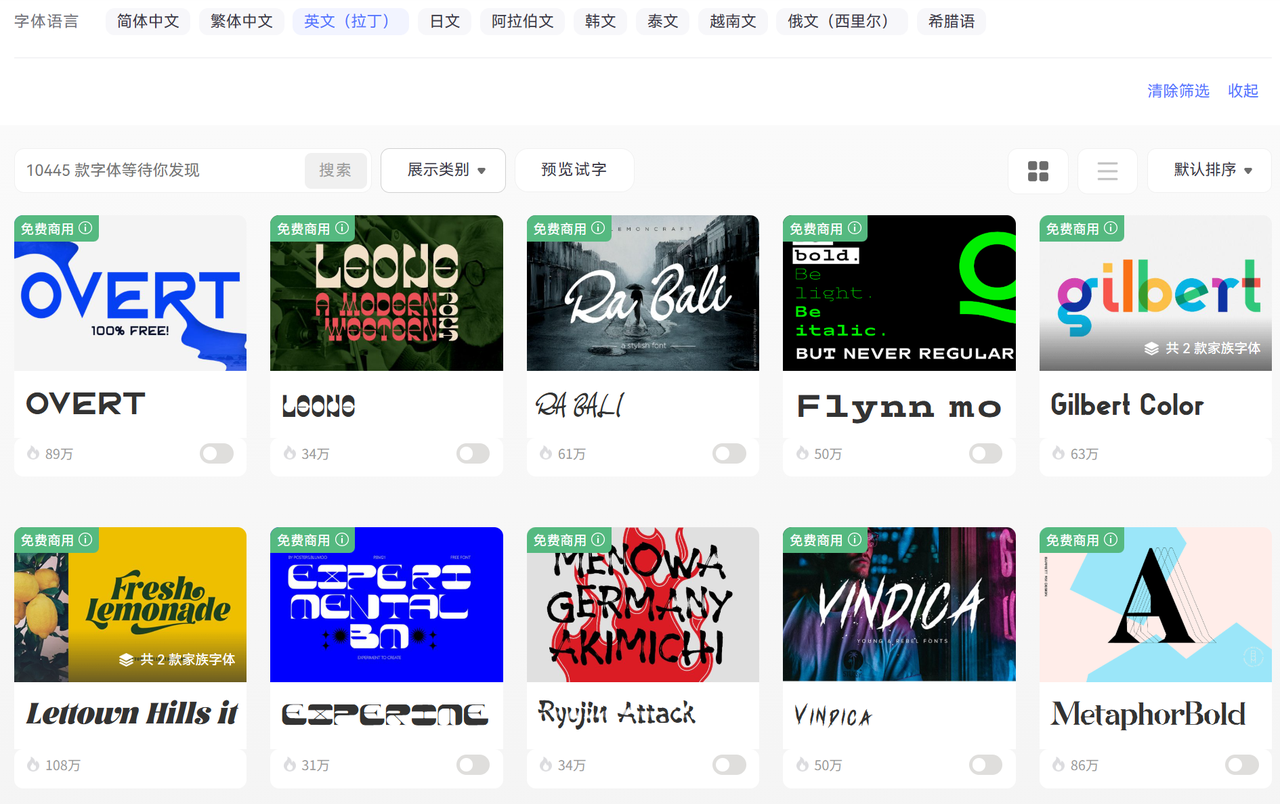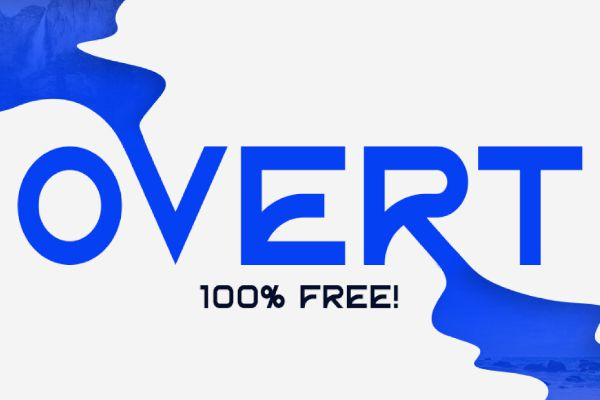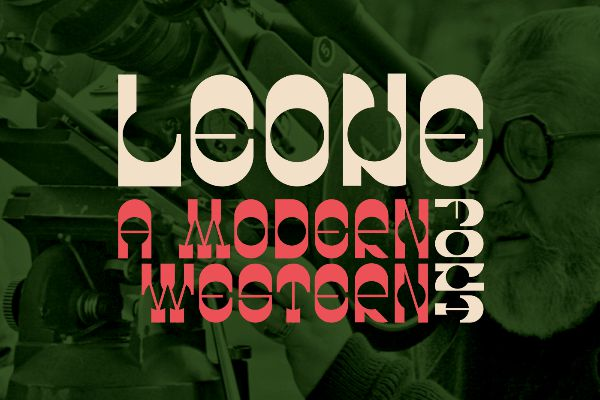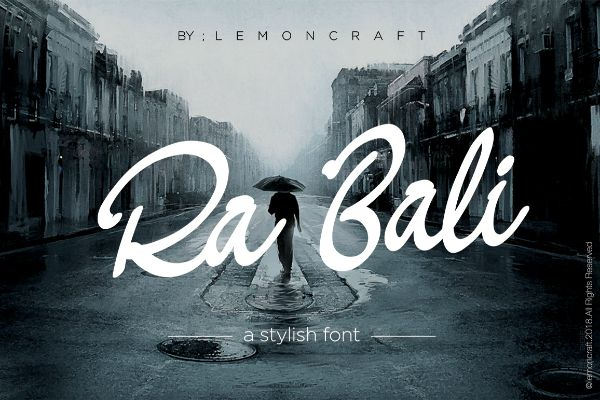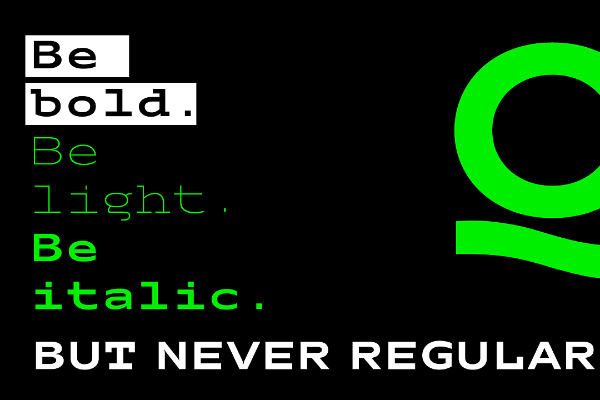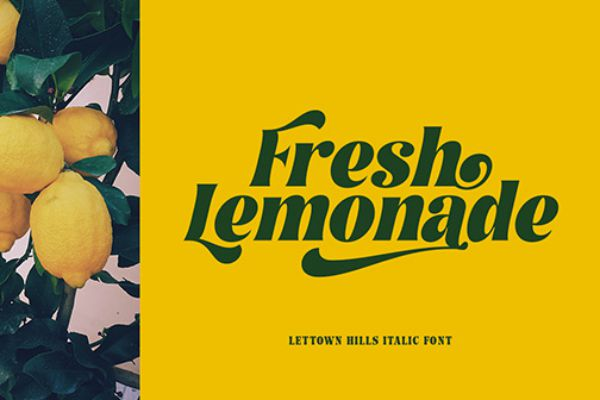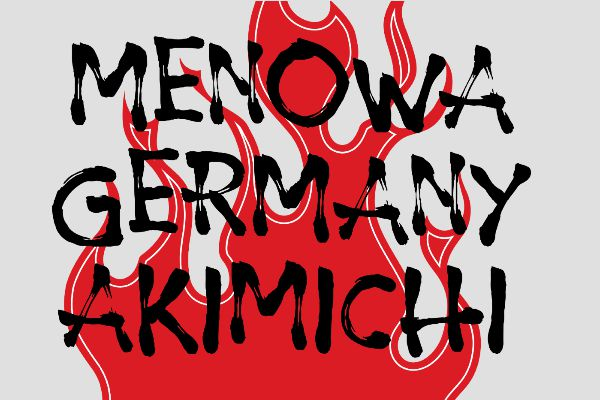
英文字体可以商用吗,分享 10 款免费商用的英文字体
不知道是否有小伙伴和我一样,觉得中文字体大部分都不可以免费商用,思考英文总不会有版权风险吧?其实都一样,大多数字体都是需要付费授权的,不能免费商用。不过今天我会给大家分享10 款可以免费商用的英文字体。
什么是英文字体
当我们谈论“英文字体”时,我们不仅仅是指一套西文字符集,更是在探讨一种蕴含文化、历史和设计哲学的视觉语言。英文字体主要可以划分为以下几大类,衬线体(Serif)、无衬线体(Sans-serif)、手写体、艺术字体,每一类都有其独特的性格和适用场景。比如手写体的英文字体适合用于邀请函、证书、品牌标识;艺术体的英文字体不适合大段文字,更适合作为标题、短语或品牌元素。
英文字体可以商用吗?
在字体选择上,最容易被忽视也最关键的一点就是字体授权。英文字体和中文字体一样,受版权法保护,不能随意的商用。
未经授权使用英文字体进行商业活动,可能面临高额的赔偿和法律纠纷。因此,在使用任何字体之前,务必仔细阅读其许可协议,确保其符合你的使用需求。宁可多花时间核实,也不要抱有侥幸心理。
10 款免费商用的英文字体
1. Overt
Overt是一款现代、简洁的无衬线字体家族,Overt笔画多采用直线和圆弧,字形结构严谨,无论大小写,字形都保持了极高的可读性,尤其适合屏幕显示和排版。整体风格简洁大方,没有过多装饰,使其具有很强的包容性和适应性,能与多种设计风格匹配,是我个人比较喜欢这款简单的字体。
1. Leone
Leone是一款优雅且具有现代感的衬线字体。Leone笔画粗细对比明显,增加了字体的优雅感和视觉冲击力。Leone字母的曲线处理流畅自然,整体呈现出一种流动的美感。对比 Overt 来说,Leone 就更“时尚”一些了。
1. RA BALI
RA BALI通常是一款充满异域风情和艺术气息的装饰性字体,RA BALI设计融入了东南亚文化的元素,具有独特的地域特色。笔画可带有独特的装饰或纹理,视觉效果丰富。辨识度高,能够快速营造特定的文化氛围或主题。
1. Flynn mono VF
Flynn mono VF是一款现代的、可变字体的等宽字体。所有字符宽度一致,便于代码编写、表格对齐和技术文档的排版,视觉整齐划一。尽管是等宽字体,但设计上仍注重可读性,确保长时间阅读的舒适度。
1. Gilbert
Gilbert字体是一款免费可商用的显示字体。字体可以呈现多色分层效果(虽然也可以是单色),灵感来源于彩虹旗,象征多元与包容。设计风格独特,富有表现力,能够快速吸引眼球并传达强烈的信息。
1. Lettown Hills
Lettown Hills是一款具有优雅手写感的现代书法字体。Lettown Hills字母之间自然连接,模拟手写时的连贯性,富有动感。保留了手写体的独特韵味和自然感,增加了亲和力。
1. Experimental Bm
Experimental Bm是一款科技感十足的字体。Experimental Bm融入赛博朋克、故障艺术(Glitch Art)或未来科技感元素。让字体具备视觉艺术效果的同时,又具有很强的表现力。
1. Ryujin Attack
Ryujin Attack是一款充满力量感和动感的显示字体,Ryujin Attack笔画通常带有尖锐的边缘或切角,字形粗壮有力,充满爆发力。字母结构带有倾斜或流线型设计,营造出速度和动态效果。
1. Vindica
Vindica通常是一款具有强烈视觉存在感的衬线字体,是一款多功能且富有表现力的衬线字体。
1. Metaphor
Metaphor字体是一款现代、简洁的无衬线字体,Metaphor笔画厚重饱满,字形粗壮,具有强大的视觉冲击力,能够快速吸引眼球。